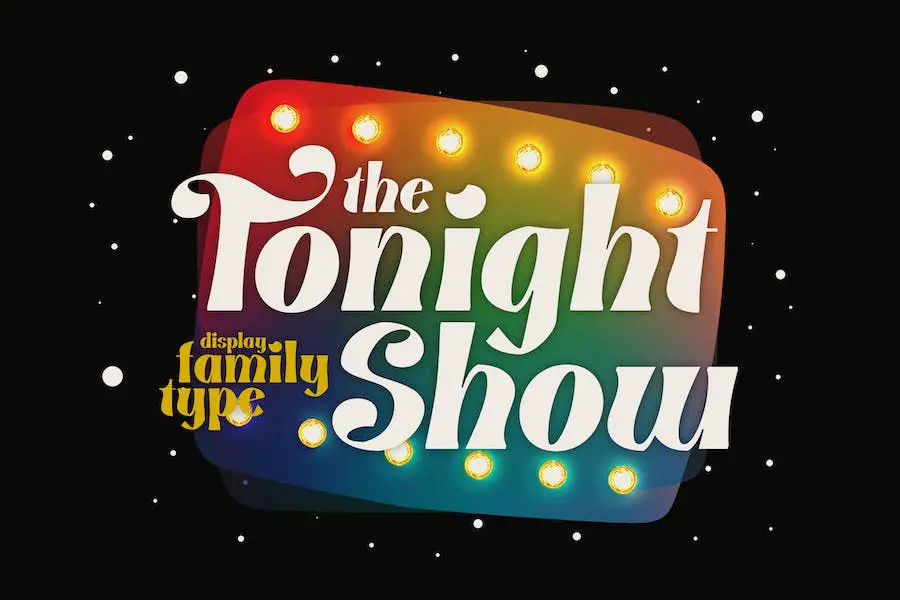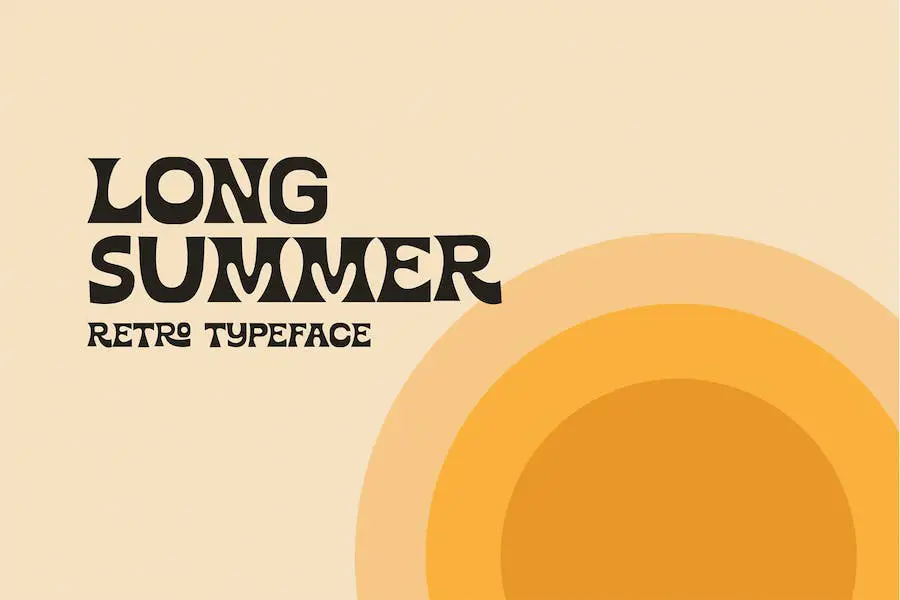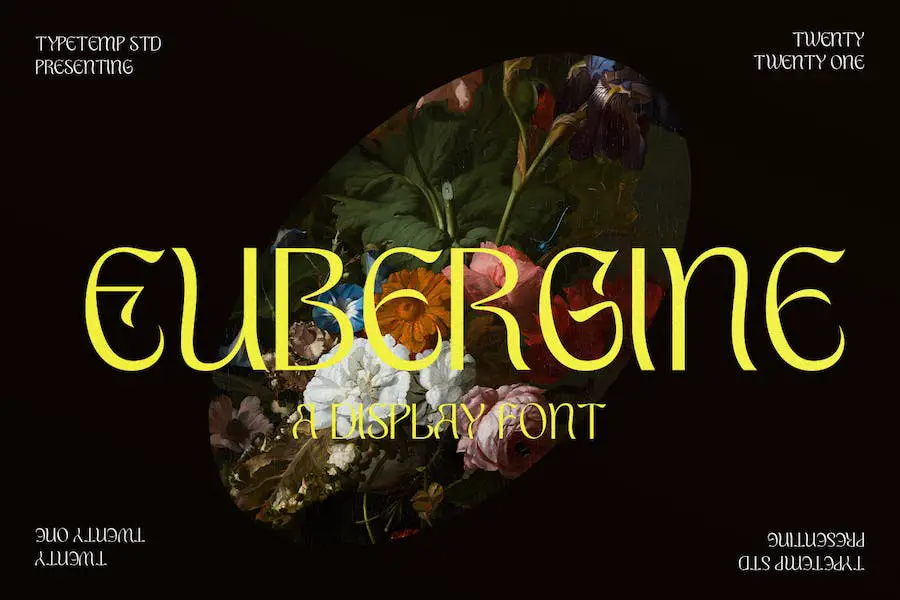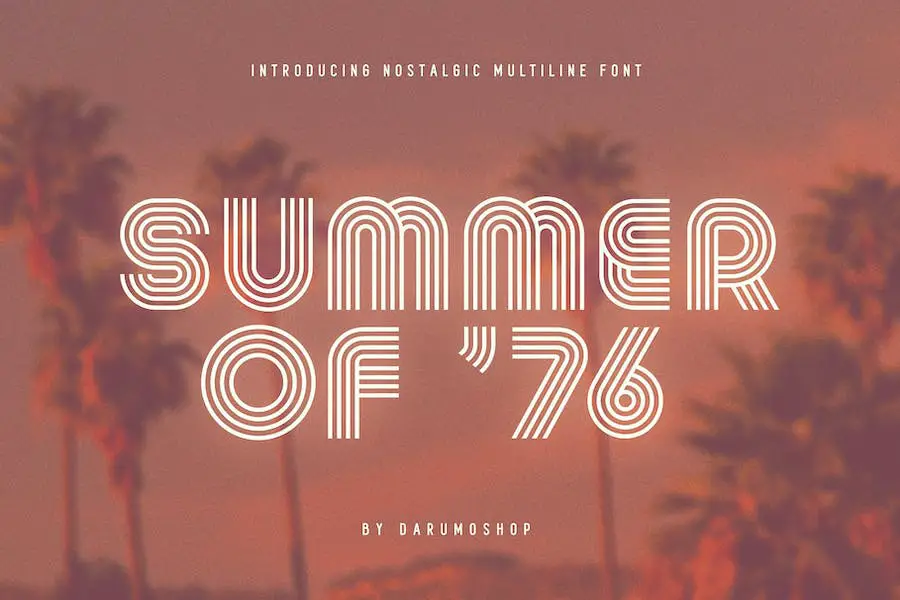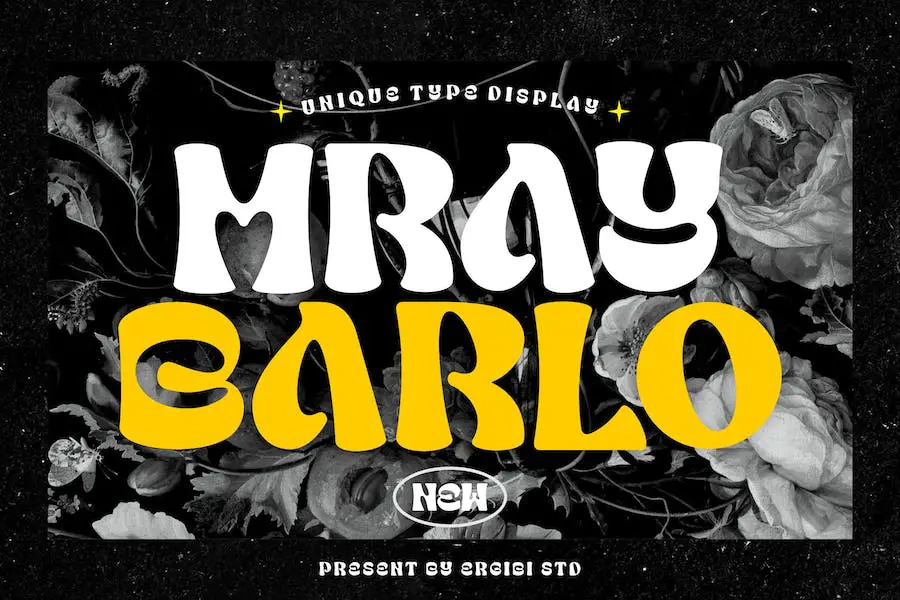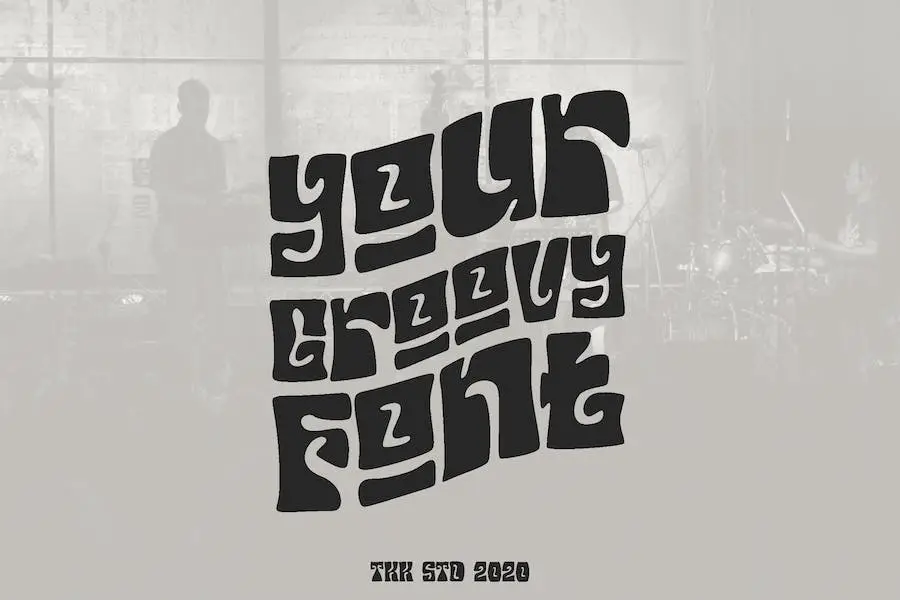
30 migliori font anni '70 del 2023 (gratuiti e premium)
Pubblicato: 2023-07-25Vuoi aggiungere un tocco vintage ai tuoi disegni? Sei curioso dello stile tipografico degli anni Settanta? Non cercare oltre perché questo post sul blog riguarda i caratteri degli anni '70.
In questo articolo esploreremo la tipografia funky e groovy degli anni Settanta che sta tornando in auge nel design moderno. Imparerai la storia dei caratteri degli anni '70 e come sono diventati un simbolo di una rivoluzione culturale.
Sapevi che gli anni Settanta sono stati un decennio di sperimentazione e libertà, e la tipografia non ha fatto eccezione? Con l'aiuto dei caratteri degli anni '70, i designer sono stati in grado di esprimersi e distinguersi dalla massa.
Quindi, facciamo un viaggio nella memoria e scopriamo come i font anni '70 possono aggiungere un tocco di nostalgia e personalità ai tuoi progetti. Forniremo un elenco dei caratteri degli anni '70 più popolari, insieme ad esempi di come possono essere utilizzati in vari progetti di design.
Quindi, preparati a fare rock and roll con qualche ispirazione tipografica di gran lunga!
I migliori font premium degli anni '70
I Sooky anni '70
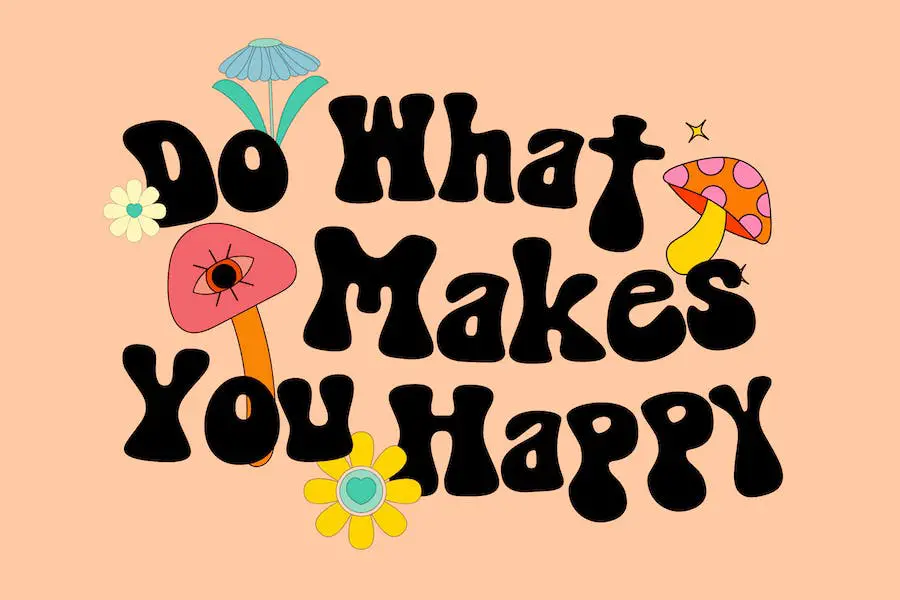
Il carattere Sooky 70s, noto anche come It Font, è un carattere frizzante divertente e giocoso con un tocco retrò alla moda. Ispirato allo spirito degli anni '70 e '90, questo font aggiunge un tocco di dolcezza a qualsiasi progetto.
Perfetto per merchandising, poster, riviste, t-shirt e altro ancora, il font The Sooky 70s farà risaltare i tuoi design. La natura frizzante e giocosa del font lo rende ideale per progetti che richiedono un tocco divertente e spensierato.
Rambors
Rambors è il font perfetto per valorizzare i tuoi design contemporanei con un tocco di nostalgia. Ispirato agli anni '70, questo font per display multilinea offre una grafica futuristica e divertente ai tuoi progetti.
È un font tutto maiuscolo con più opzioni maiuscole e minuscole, che offre immense possibilità di esplorare vari design.
Questo carattere accattivante è ottimo per titoli su poster, volantini, grafica animata e adesivi. Il carattere si completa con un carattere alternativo che aggiunge un ulteriore livello alla tua tipografia.
Giorno alla moda
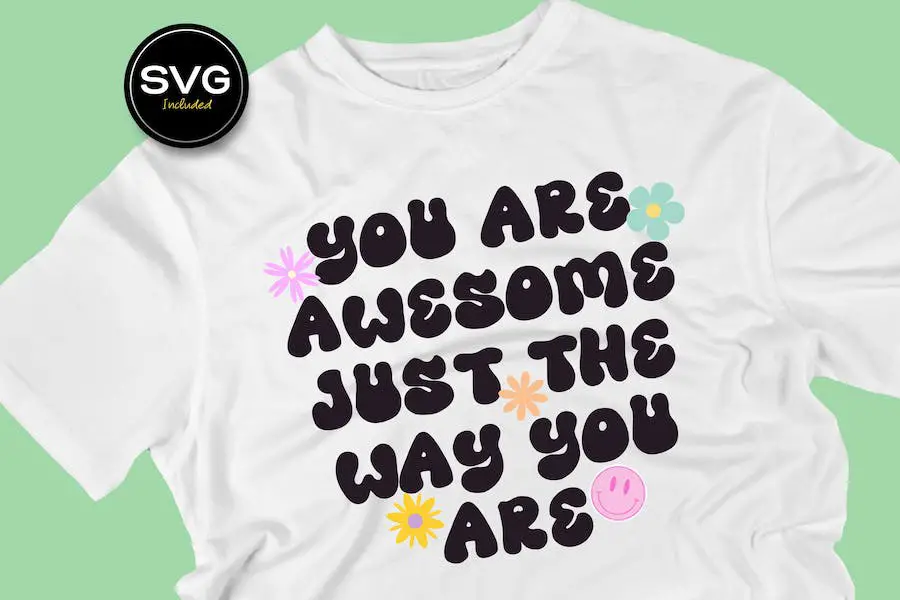
Groovy Day è un font scritto a mano retro-moderno con un aspetto bizzarro e giocoso. I tratti naturali di questo carattere creano un'atmosfera carina e casual perfetta per una varietà di progetti.
Puoi unire questo carattere con il carattere More Sugar per creare un layout giocoso, titoli solidi, titoli forti, loghi e altro ancora. Groovy Day è disponibile nei formati OTF, TTF, WOFF e SVG (singoli caratteri).
Questo tipo di carattere è più adatto per copertine di libri, poster, loghi, magliette, artigianato e merchandising, libri per bambini, cartelli murali e molti altri progetti correlati.
Il pacchetto di font include tutto il necessario per iniziare il tuo prossimo progetto di design. Il carattere Groovy Day darà un aspetto audace e giocoso ai tuoi progetti facendoli risaltare.
UNI Nord
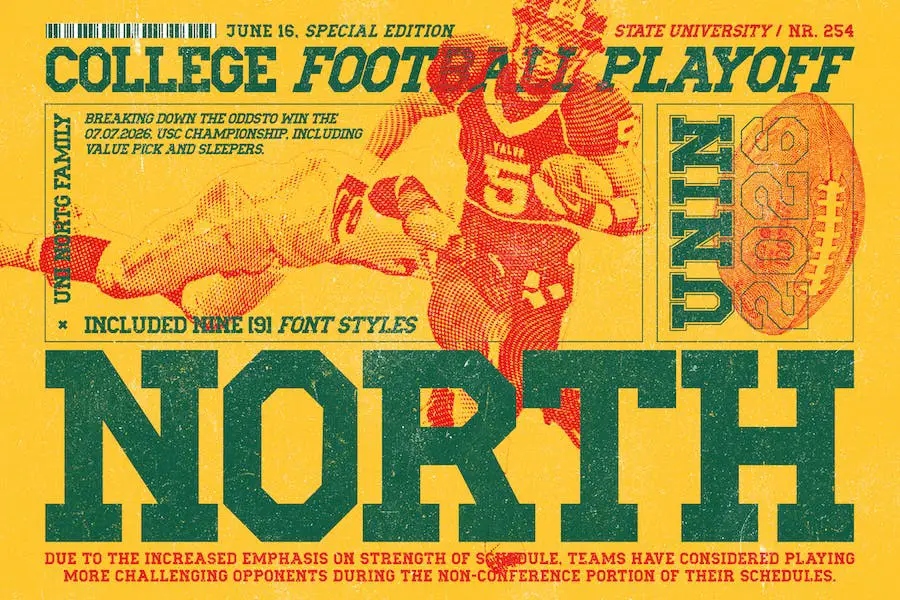
UNI North è un font serif vintage e slab realizzato a mano ispirato a sport universitari, poster retrò, cartoline e pubblicità dagli anni '70 agli anni '90. È disponibile in 9 stili, incluse le varianti Regular, Italic e College.
Il carattere è perfetto per scale grandi e dimensioni in punti più piccole e presenta alternative stilistiche, legature e caratteri internazionali. È inoltre ottimizzato per il testo visualizzato, la stampa, le interfacce utente, i dispositivi mobili, il web design e i poster.
UNI North offre supporto multilingue per molte lingue, rendendolo la scelta ideale per qualsiasi layout di progettazione. Per accedere alle lettere alternative aggiuntive, utilizza il pannello dei glifi in programmi come Adobe Photoshop CC 2015, Adobe Illustrator e Adobe Indesign.
Grandtown
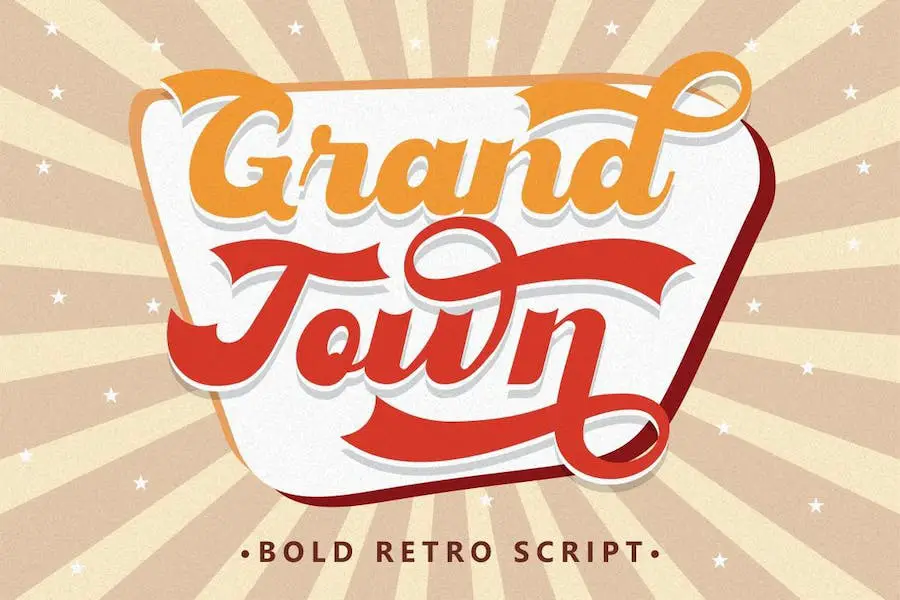
Grandtown è un font in stile retrò ispirato alla tipografia e al lettering degli anni '70 e '80. Vanta una tipografia audace che integra perfettamente design vintage e retrò, badge, loghi, poster, branding, packaging, segnaletica, copertine di libri e molto altro.
Il carattere è codificato PUA, presenta numeri e segni di punteggiatura e viene fornito con molte alternative, il che semplifica la personalizzazione e la creazione di caratteri fantastici. Supporta anche più lingue.
L'installazione di Grandtown è un gioco da ragazzi e offre sia opzioni minuscole che maiuscole, nonché alternative e legature OpenType. Con Grandtown, non solo aggiungerai un tocco retrò ai tuoi design, ma li farai anche risaltare con questo carattere audace e unico.